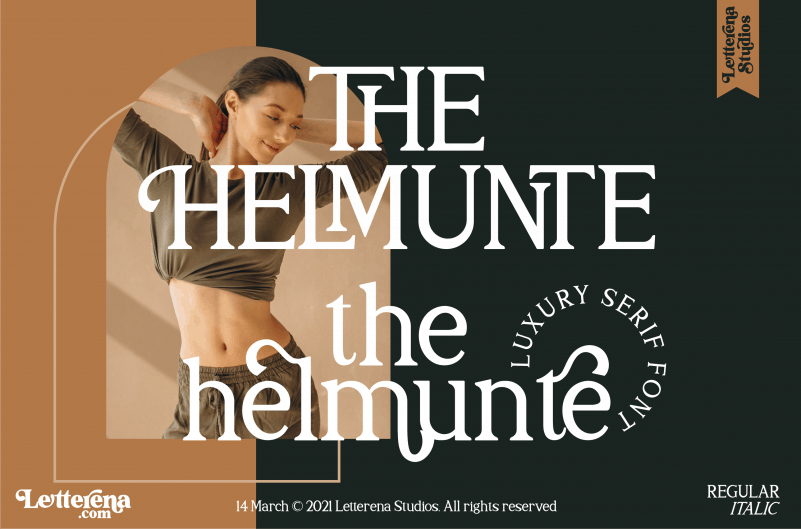
A THE HELMUNTE Serif Font é uma escolha perfeita para quem busca agregar sofistica e elegância a seus projetos visuais. Esta tipografia serif é ideal para criações que exigem um toque de luxo, sejam elas para logotipos, identidade visual, design de embalagens ou até mesmo para itens de consumo diário como mugs e sacolas. A THE HELMUNTE oferece uma sensação de qualidade que se impregna em todos os projetos elegantes onde é utilizada. Seja no campo da moda, como na criação de roupas personalizadas ou adesivos para produtos finos, ou até mesmo em design gráfico tradicional, a THE HELMUNTE traz um toque sofisticado que torna qualquer projeto um luxo e encanto visual. Além disso, seu uso permite uma vasta gama de aplicações, desde cartões de nome até cartões de convidados e capas de livros, tudo isso mantendo aquela sensação de elegância que caracteriza a THE HELMUNTE Serif Font.